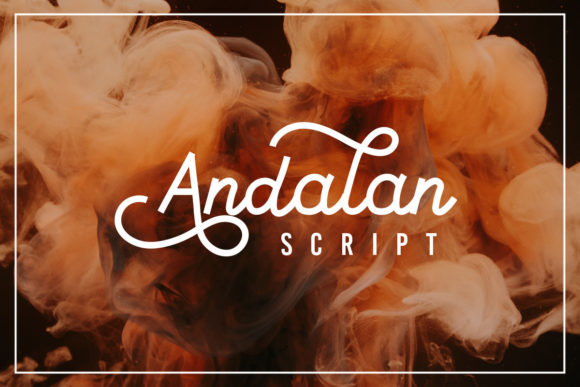
Creativefabrica Andalan Script Font
[Creativefabrica] Andalan Script Font
Andalan Script - это нежный, плавный и винтажный рукописный шрифт.
Не слишком тонкий и не слишком толстый, сбалансированный и разнообразный, этот шрифт создан для того, чтобы подчеркнуть красоту ваших проектов.